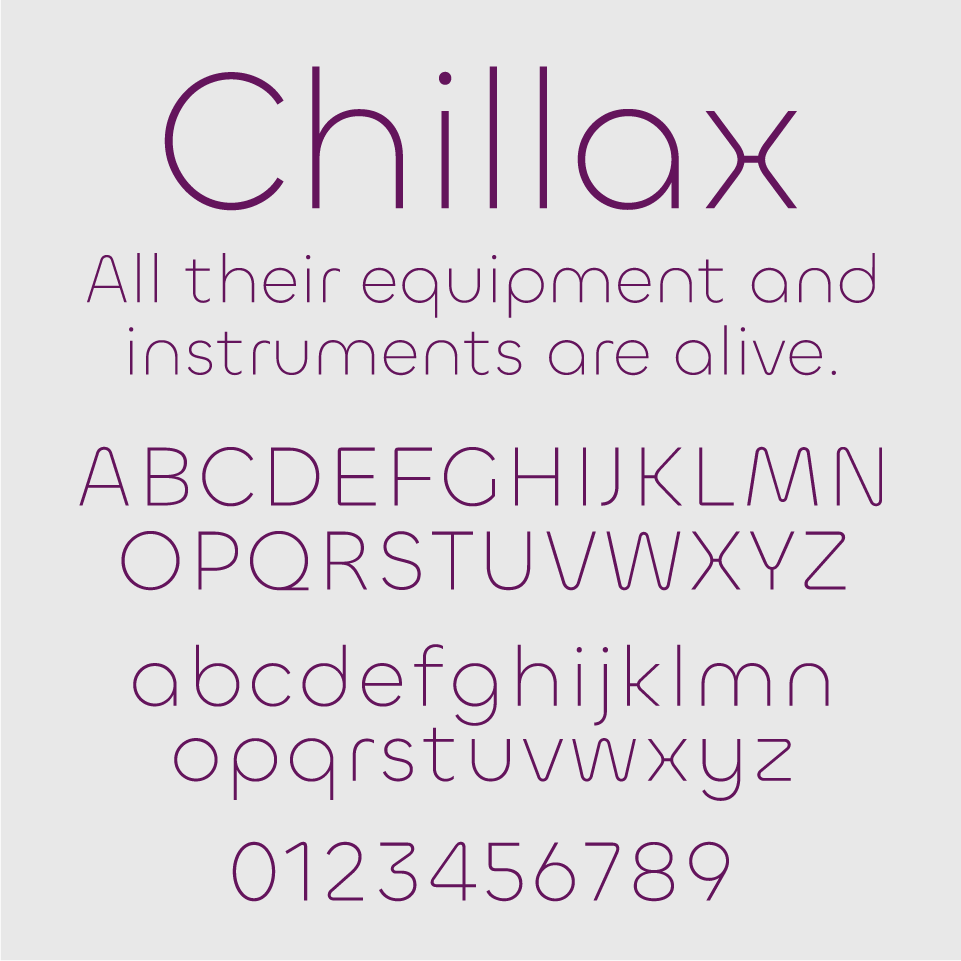
Chillaxフォントは、幾何学的でコンパクトな字形と、ゆるやかなラウンドが組み合わさった、名前の通り“チル”な空気がただようサンセリフフォントです。ほどよい余白感と整ったリズムが、静けさと安心感を与えてくれます。
フレンドリーな雰囲気がありながら、現代的でシンプルな印象もあり、UIデザインやスマートな印象のロゴにもぴったり。絶妙な丸みを帯びたフォルムは、読みやすさと心地よさを両立したフォントです。